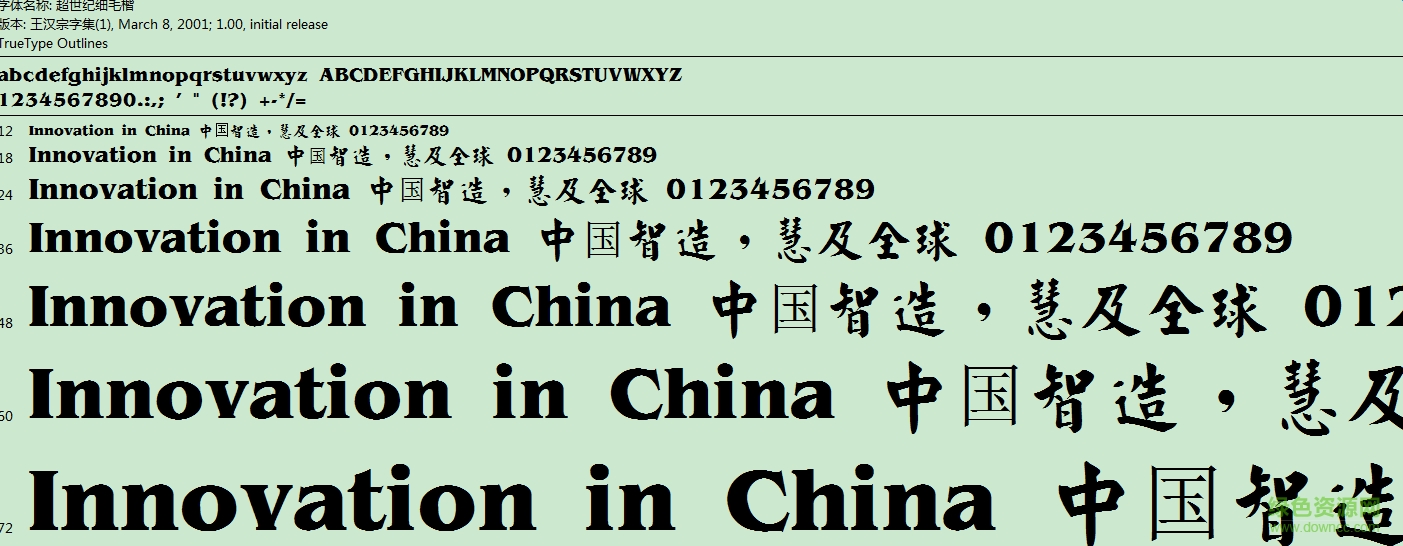
超世纪细毛楷
超世纪细毛楷字体是一款楷体字体,适用于广告艺术设计等方面,而且整个字体使用起来十分的大气,整体排版效果也非常的不错,有需要的朋友可以来绿色资源网免费下载哦!更多楷体字体等你来发现。
字体特色
一般用于书籍的前言与图片的注解部分。在副标题和广告(产品)解说(说明)部分运用的比较多。的传统韵律比较强,所以在传统类的设计对象中运用的非常广,但是是不会作为主标题的文字选择。
如果从设计的纯角度来讲,运用的也是非常少的。笔画很均匀并且撇撩笔画不尖,使人易于阅读。由于其醒目的特点,常用于标题,导语,标志等等。当然常见的标题、导语采用的是方正字库里的粗黑,大黑,中黑,而不是我们WINDOWS里自带的。